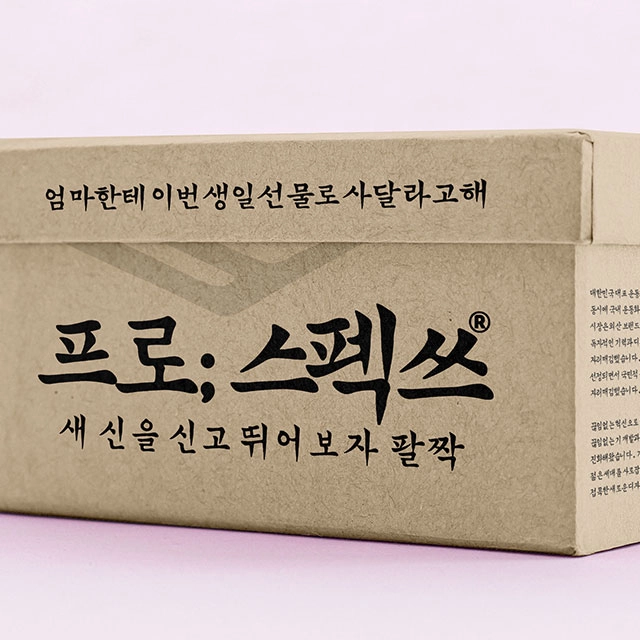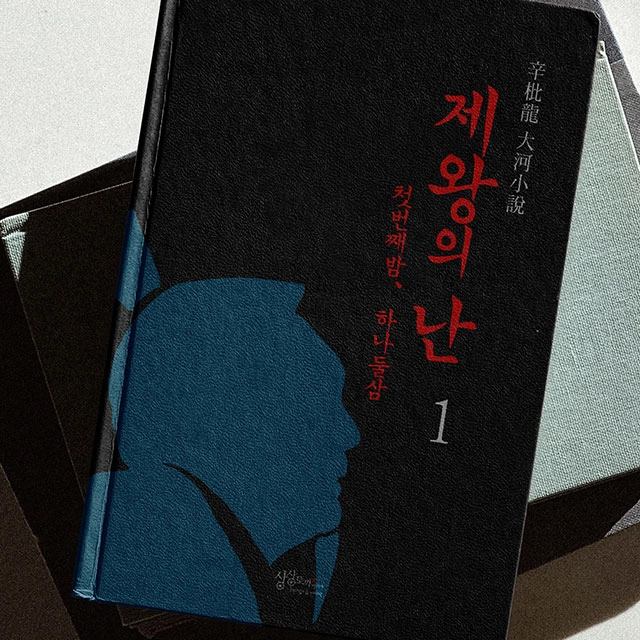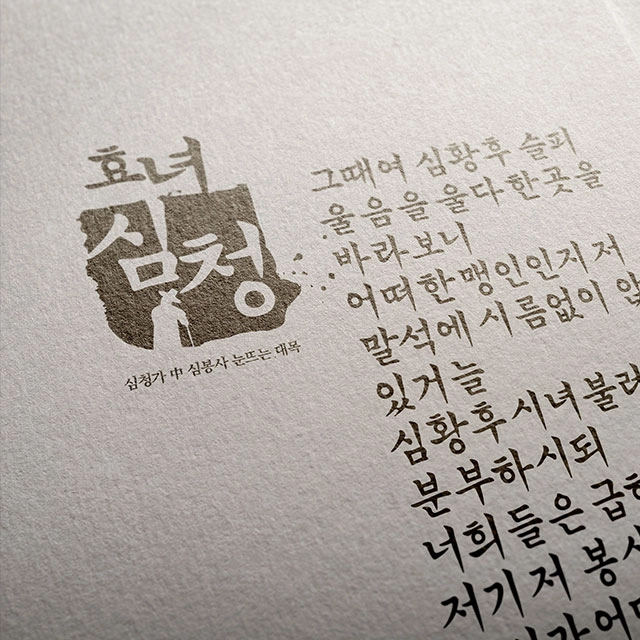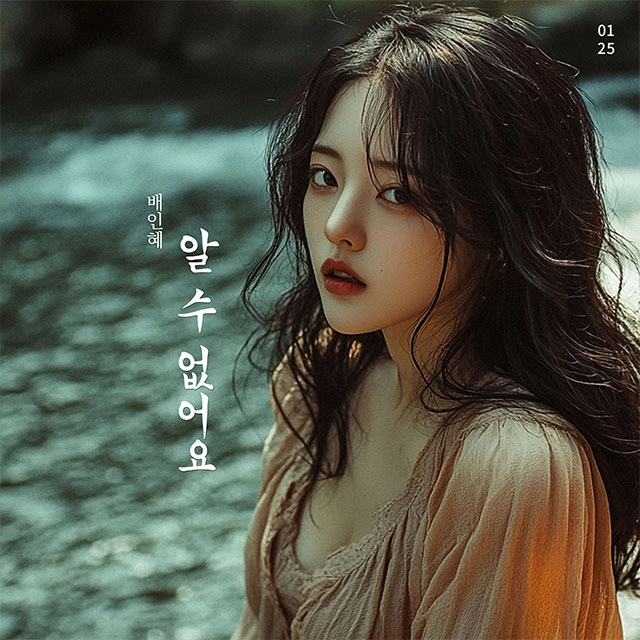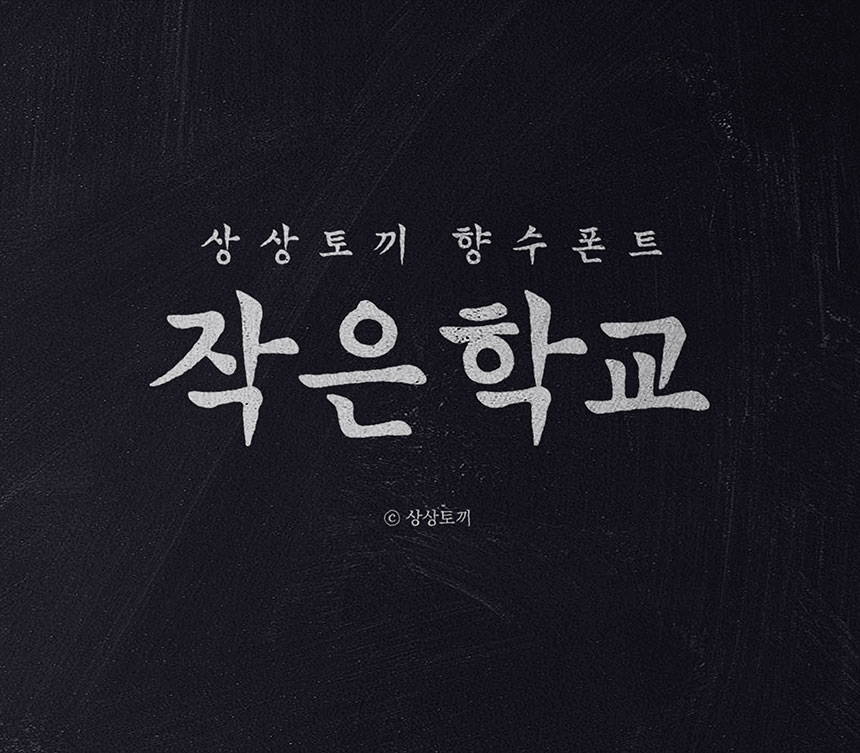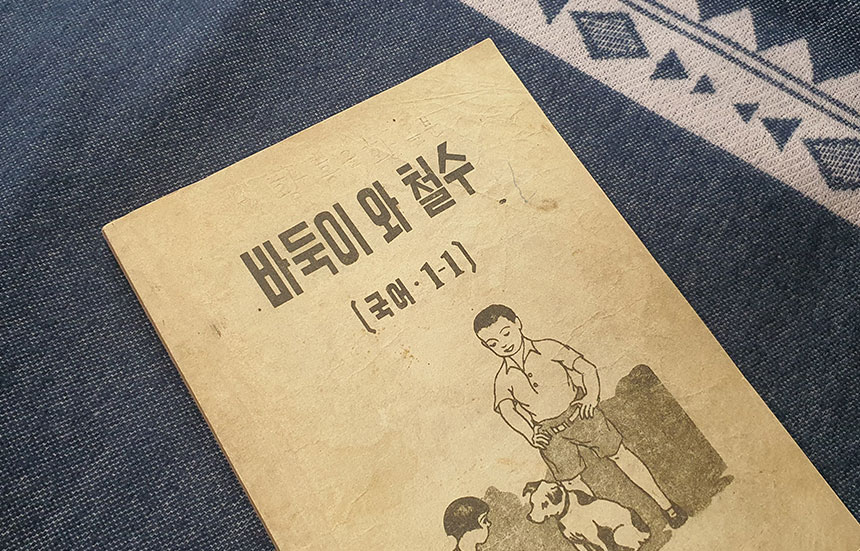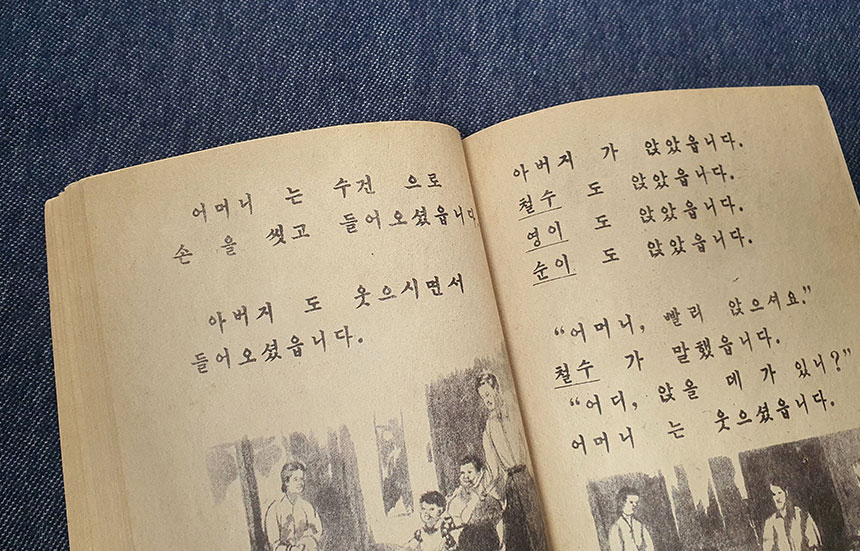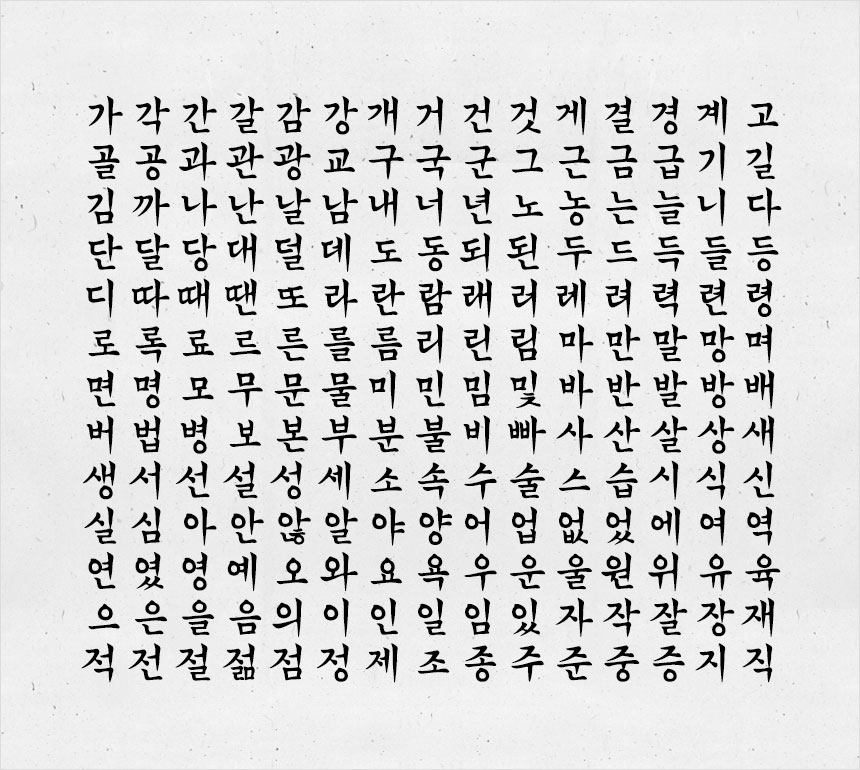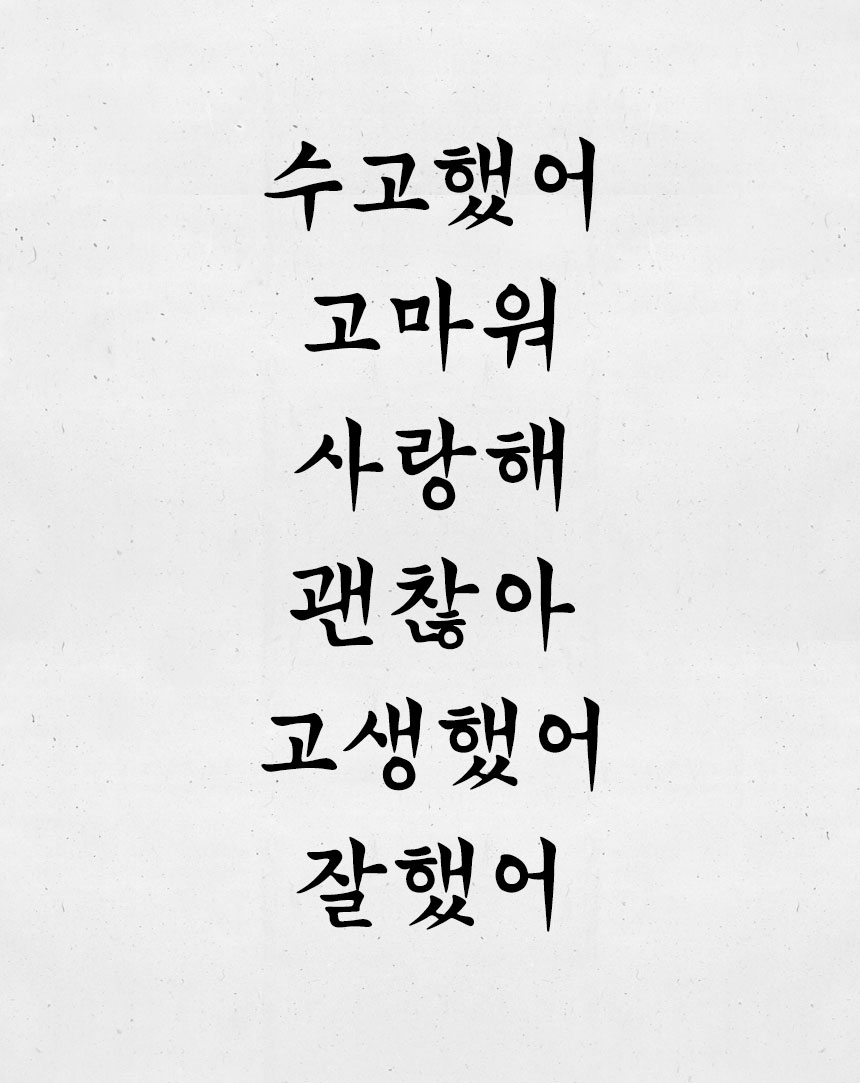
작은학교 레귤러
레트로 감성을 가득 담은 폰트, 작은학교 레귤러
바둑이와 철수를 기억하시나요?그 시절, 우리의 교실은 나무 책상과 분필 냄새로 가득 차 있었습니다. 교실 뒤편에 놓인 큰 석탄 난로, 그리고 벽에 걸린 국어 교과서 표지는 지금도 많은 이들에게 따뜻한 추억으로 남아 있습니다.
<작은학교>는 1970년대의 초등학교 교실로 우리를 데려다주는 특별한 레트로 폰트입니다. 과거 국어 교과서의 본문에서 사용되었던 글자체를 현대적으로 재해석하여 만든 이 폰트는, 단순히 글씨체 이상의 의미를 담고 있습니다.
세련되지 못한 듯한 투박한 획은 오히려 따뜻하고 정겨운 감성을 불러일으키며, 70년대의 향수를 느낄 수 있습니다. 그 시절, 국어 시간에 썼던 글씨체가 눈앞에 다시 살아나는 듯한 생생함을 느낄 수 있습니다.
이 폰트는 당시 교과서에서 느껴지던 단정함과 친근함을 그대로 재현합니다. 글자 하나하나에 담긴 추억과 감성은 레트로한 매력을 가득 품고 있어, 다양한 디자인 작업에 독특한 분위기를 더해줍니다. 단순히 레트로한 디자인을 넘어서, 사람들의 마음속에 잠들어 있는 추억을 깨우는 특별한 역할을 합니다.
레트로한 감성을 살린 포스터나 카드, 굿즈 제작에 활용하면 과거의 따뜻한 기억을 소환할 수 있습니다. 또한 아날로그 감성을 담고 싶은 교육 콘텐츠나 추억이 깃든 개인 프로젝트에도 안성맞춤입니다. 이 폰트는 단지 디자인 도구가 아니라, 여러분의 스토리에 감동을 더하는 매개체가 될 것입니다. <작은학교> 활용 예시상상토끼가 운영하는 AllAI 뮤직 레이블 화이트래빗™의 배인혜 앨범 커버에 <작은학교>의 바탕이 된 활자 디자인의 레터링 작업이 사용되었습니다.